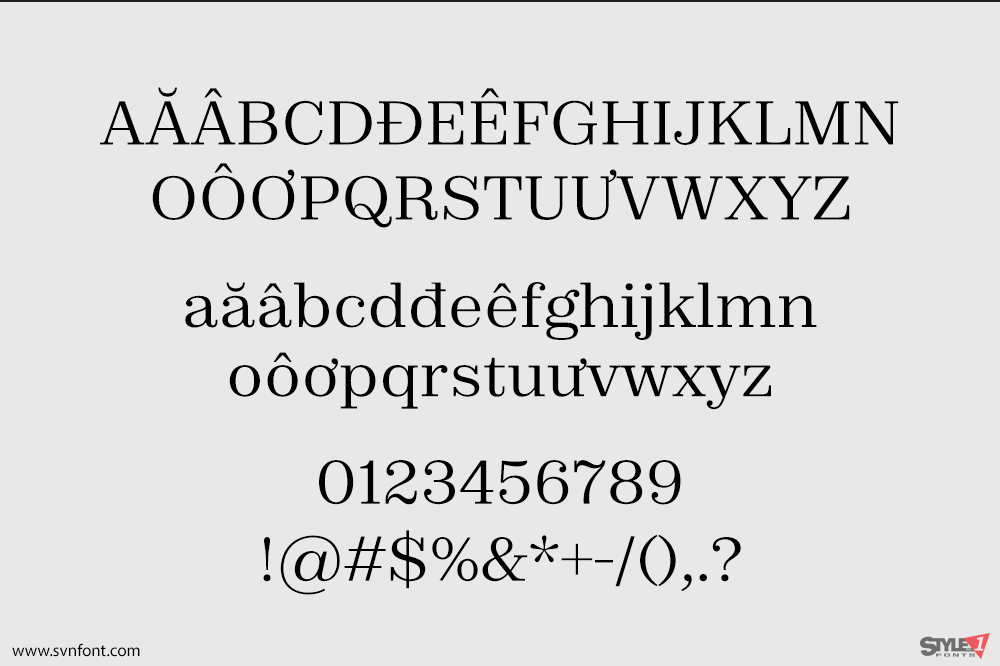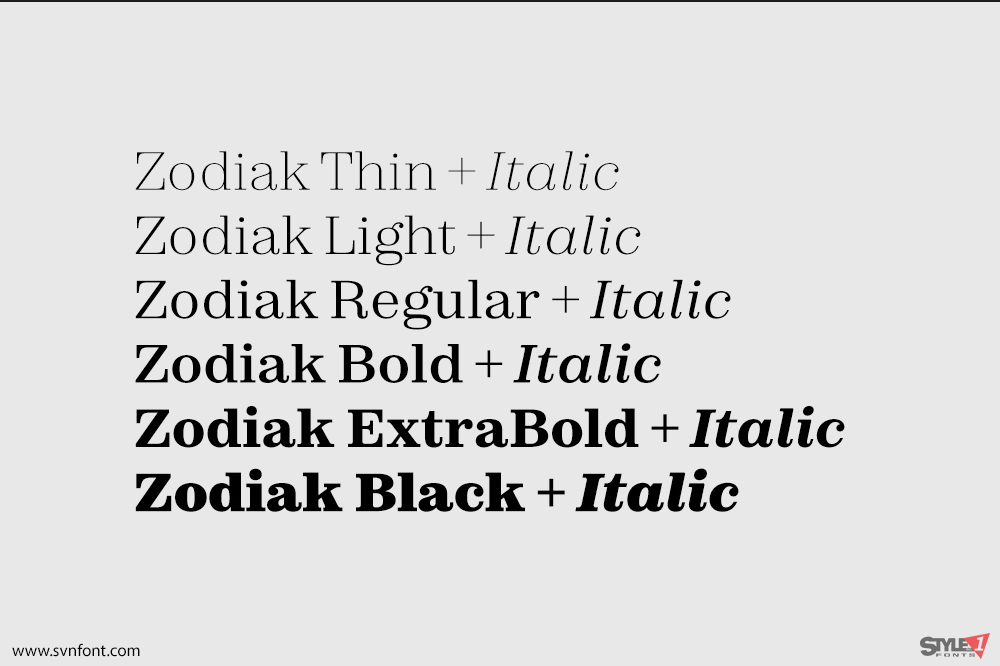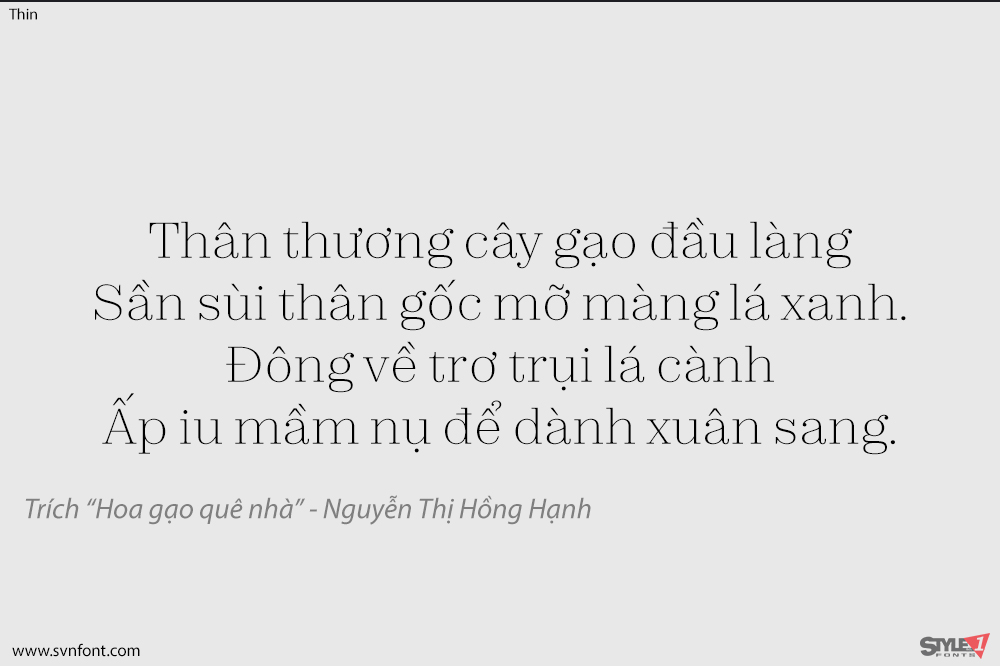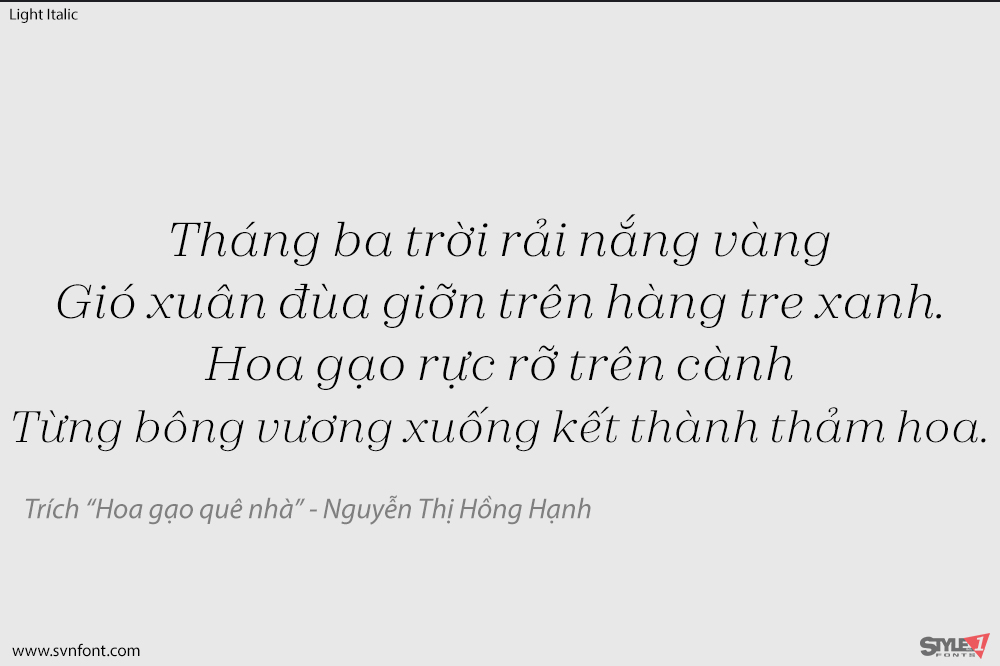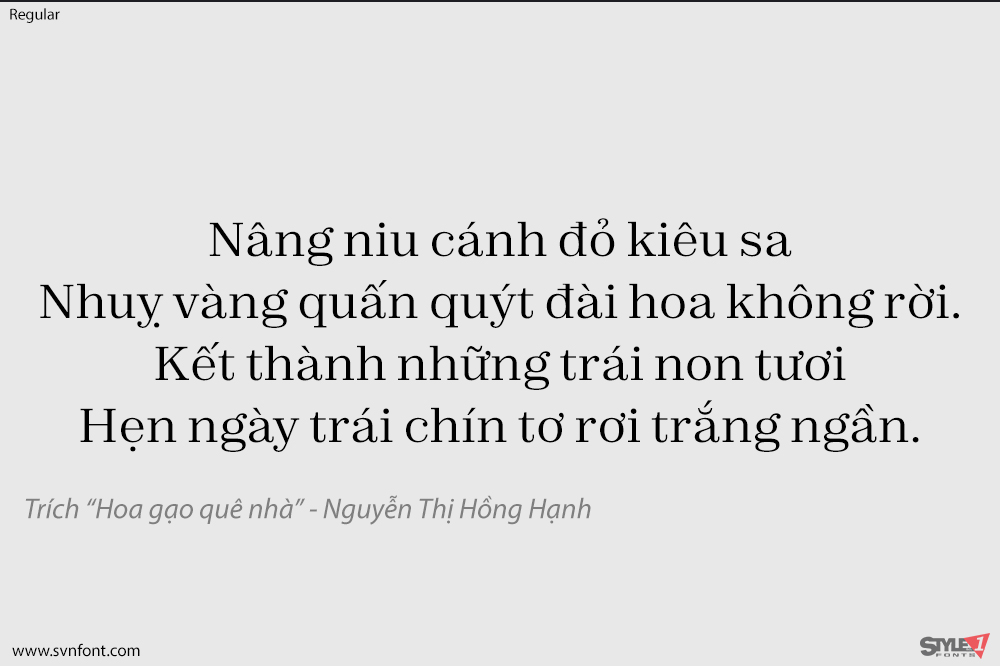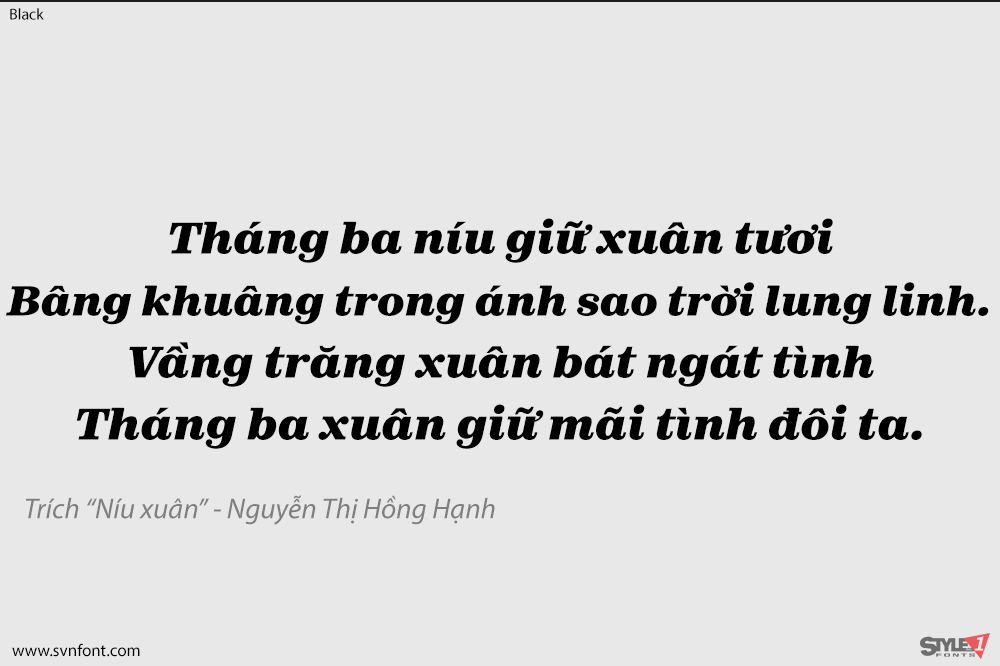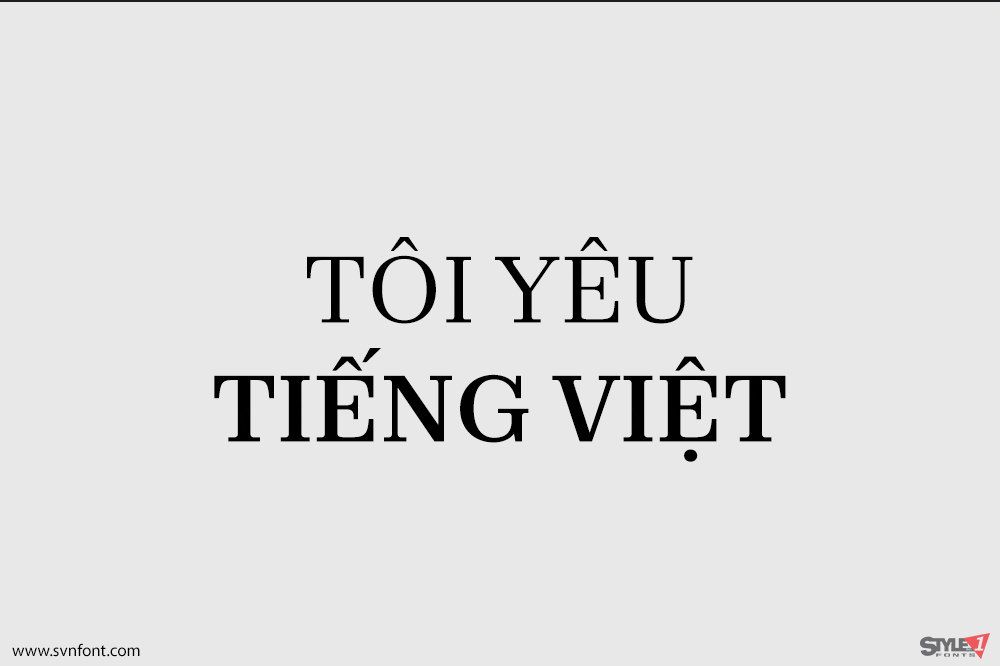
Zodiak là một họ phông chữ với các chân chữ (serif) vững chắc. Một vài độ đậm trong họ phông chữ này rất phù hợp để trình bày lượng lớn văn bản liên tục; mặt khác, các phông chữ cực mỏng và cực đậm lại kết hợp tuyệt vời trong các ứng dụng hiển thị. Hình dáng chữ cái trong Zodiak có trục dọc, và thiết kế của chúng gợi nhớ đến các phông chữ báo chí đương đại, cũng như các kiểu chữ cuối thế kỷ XIX theo mẫu Century. Zodiak bao gồm 12 kiểu, trải dài từ Thin đến Black. Mỗi độ đậm trong số sáu độ đậm này đều có một phông chữ nghiêng đi kèm. Hình dáng chữ cái của Zodiak có các chân chữ dạng tấm dày được nối liền với thân chữ. Vì tỷ lệ chữ hoa của nó mang phong cách thế kỷ XIX, nên chúng tạo cảm giác thị giác như thể tất cả đều có chiều rộng gần bằng nhau. Điều tương tự cũng đúng với các chữ số, chúng có cùng chiều cao với chữ hoa. Các chữ số bao gồm các chi tiết trang trí đẹp mắt, chẳng hạn như các nét giống như lá cờ ở dưới cùng của chữ ‘2’ và trên cùng của chữ ‘7’. Các nét kéo dài lên trên của chữ thường trong Zodiak cao hơn một chút so với đỉnh của chữ hoa và chữ số. Chiều cao x của Zodiak cũng khá lớn. Chữ ‘g’ thường trong các phông chữ đứng, là kiểu hai tầng, có một tai chữ đáng yêu vươn lên trên chiều cao x. Trong các phông chữ nghiêng, cả chữ ‘a’ và chữ ‘g’ đều là kiểu một tầng. Các hình dáng chữ nghiêng cũng có các đầu mút tròn đặc biệt nổi bật. Zodiak là tác phẩm của một nhóm các nhà thiết kế chữ có trụ sở tại Paris, bao gồm Jeremie Hornus, Gaetan Baehr, Jean-Baptiste Morizot, Alisa Nowak và Theo Guillard.
Nhà thiết kế: Jeremie Hornus, Gaetan Baehr, Jean-Baptiste Morizot, Alisa Nowak, Theo Guillard
Nhà phát hành: Indian Type Foundry